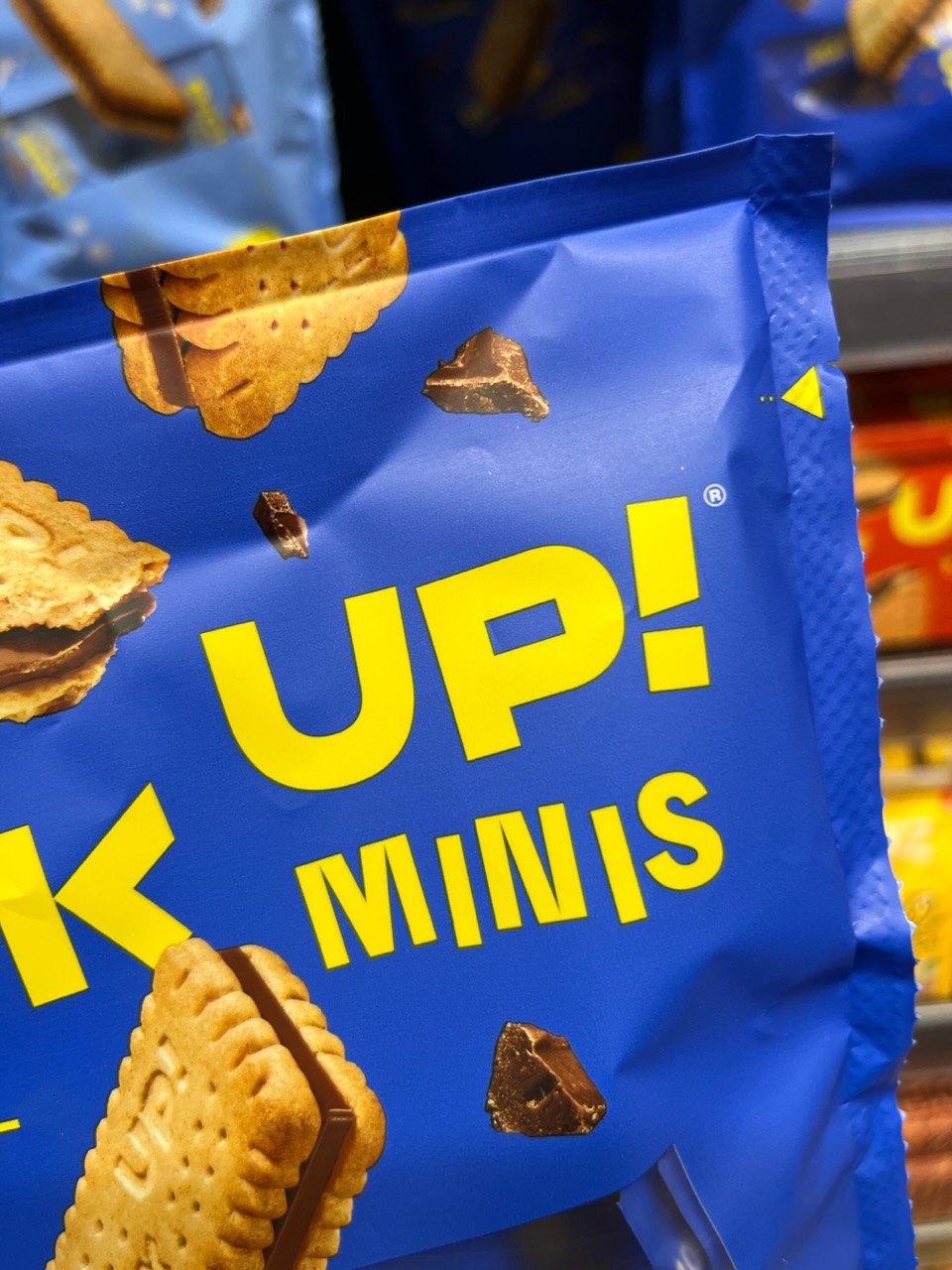
Serifenlose mit abgesägten Lettern (z.B. A, M, N, V, W ...) aka Sägewerk Grotesk
Er hat wieder in seinen Spezialfoundry-Koffer gekramt.
Das hab ich auch gedacht. Hipster-Fonts Deluxe ... :cheer:
So was kaufen die Leute? Mann, bin ich auf dem Holzweg!
Der Trend ist schon wieder am abflauen (zumindest soweit ich das nachvollziehen kann). Die Everett, die von den hier versammelten Sägewerk-Schriften wohl am alltagstauglichsten ist, war vor einiger Zeit recht omnipräsent.
Everett
Ich würde meinen, damit hat man diese Gattung auch erst richtig befeuert wenn nicht sogar ins Leben gerufen.
Der Trend ist schon wieder am abflauen (zumindest soweit ich das nachvollziehen kann).
Der Trend ist zumindest im Mainstream angekommen … :roll:
Das kratzt mich übrigens fast so wie die bei der Sendung "Vera" verwendete Typografie. Hier im statischen Bild ist es nicht so anschaulich, aber in den Titelsequenzen ergibt sich da ein eigentümlicher Effekt, wobei man die Worte ganz normal liest, sich aber dabei aber irgendwie ungemütlich und grundlos bedroht fühlt.
Artificial
Die könnte gut in die Unterkategorie »Laubsäge Grotesk« passen ...